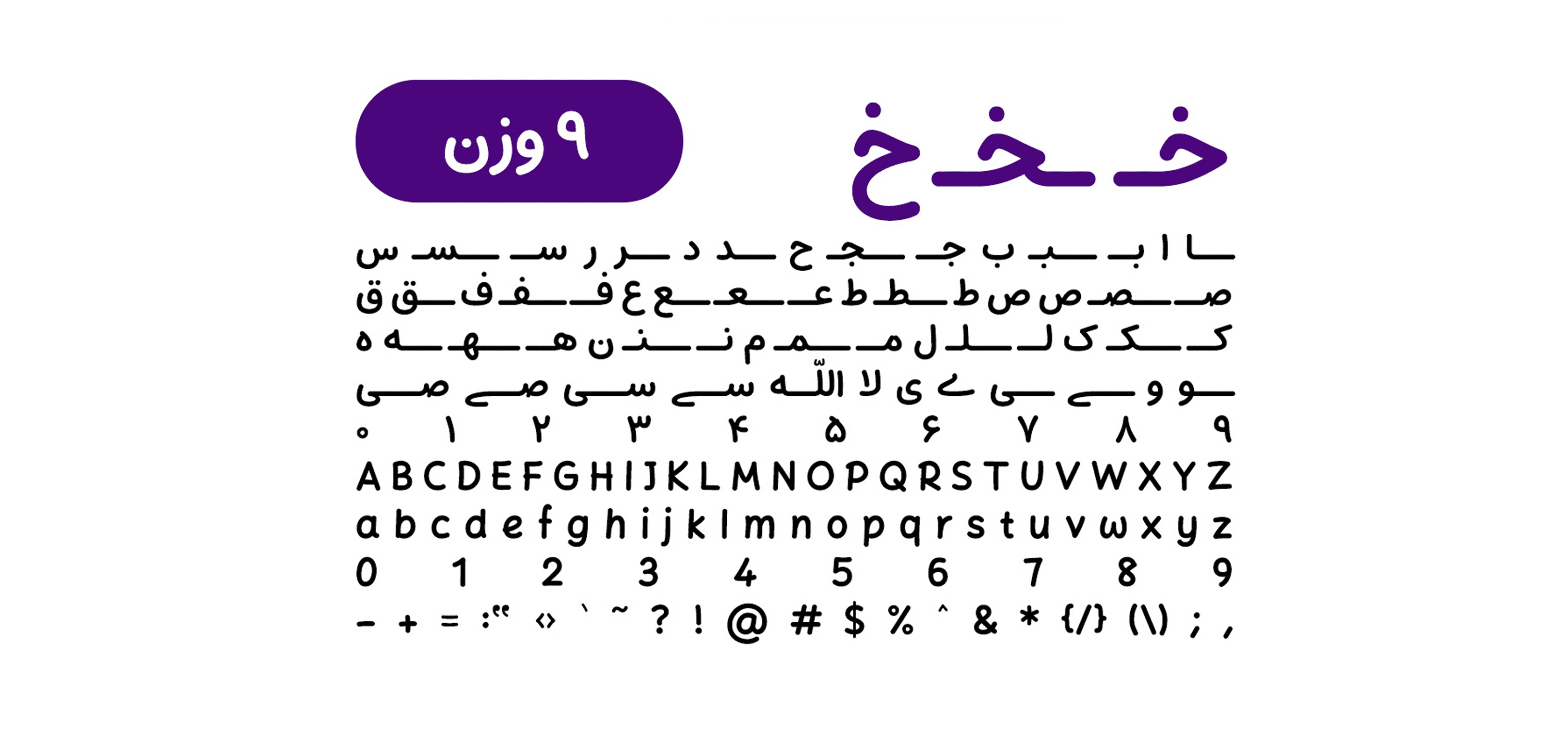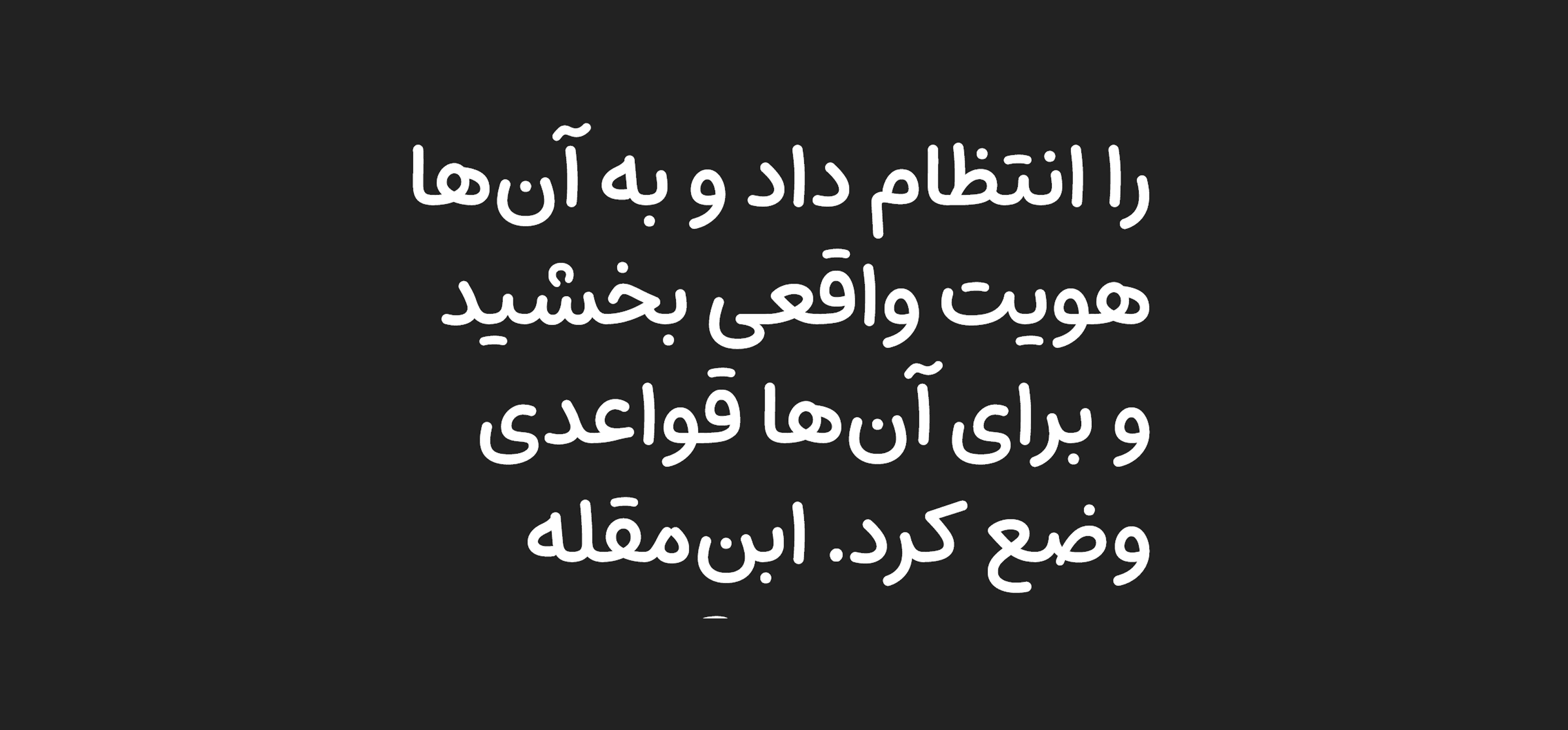
تحميل مجاني لخط "ميخك" (Mikhak) تايبفايس بـ 9 أوزان مختلفة؛
يأتي خط ميخك بثلاثة أنماط للتنقيط وبنسخة متغيّرة (Variable Font) متوافقة مع الويب، ومصمَّم خصيصًا للاستخدام في النصوص الطويلة.